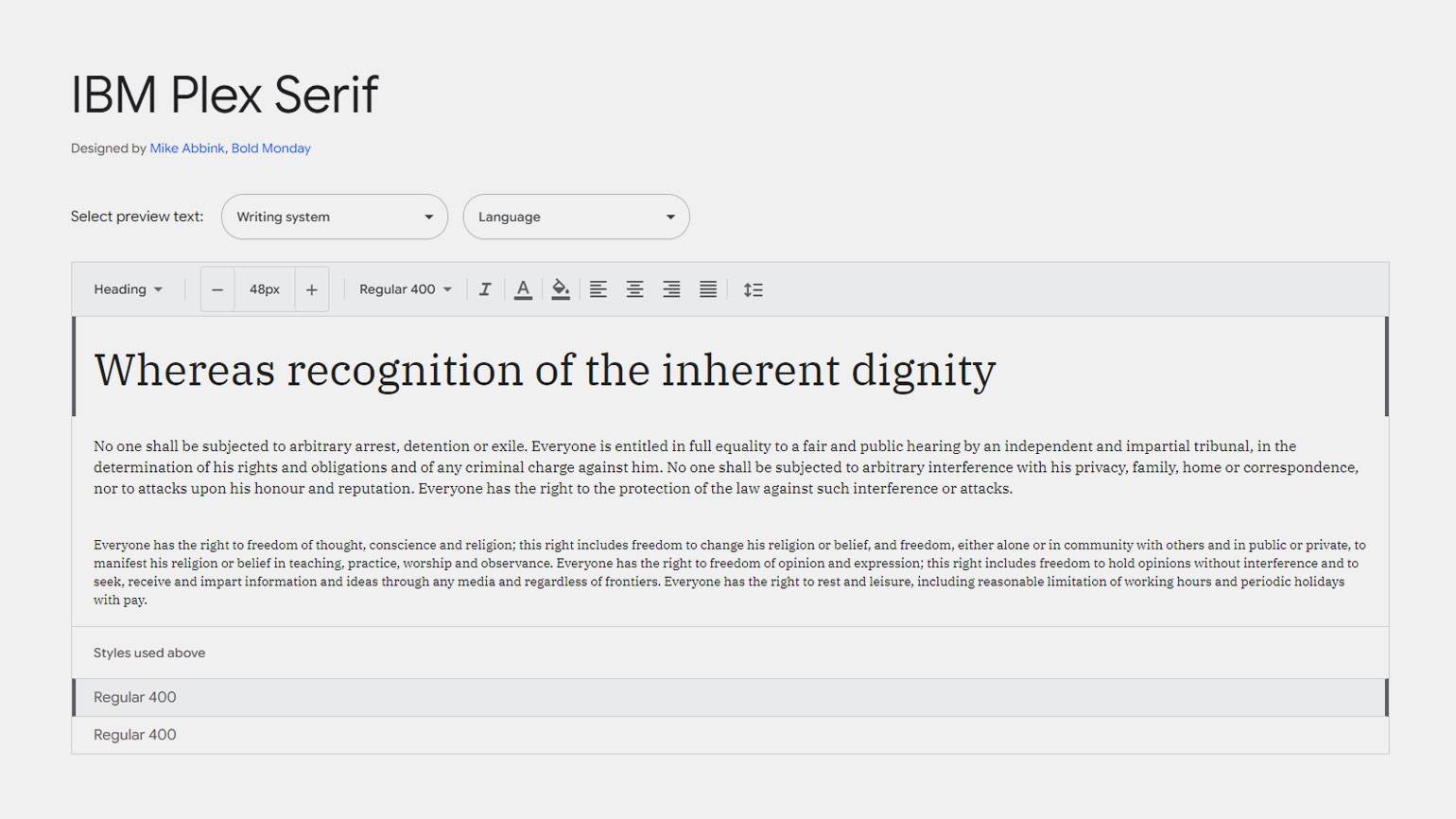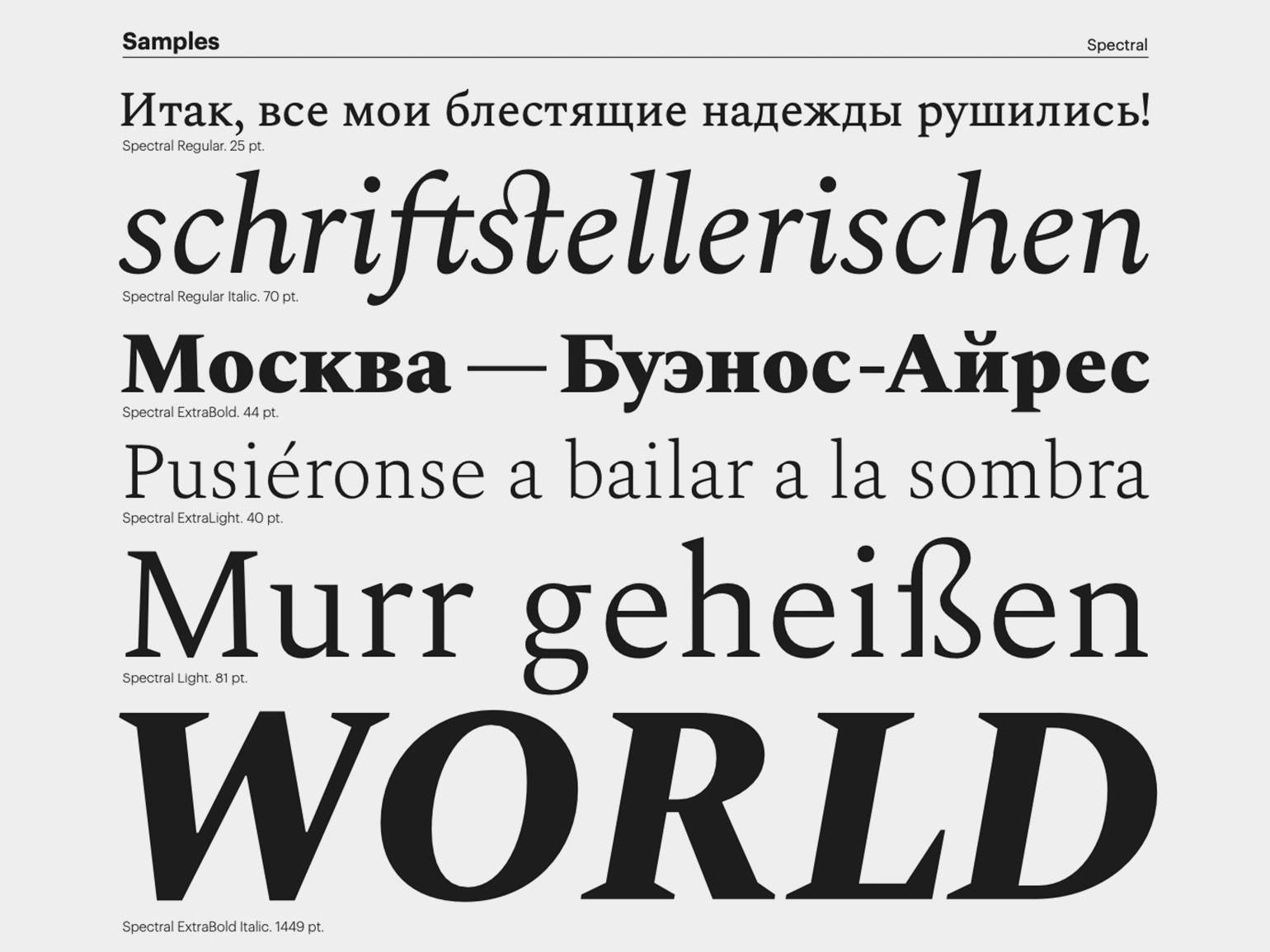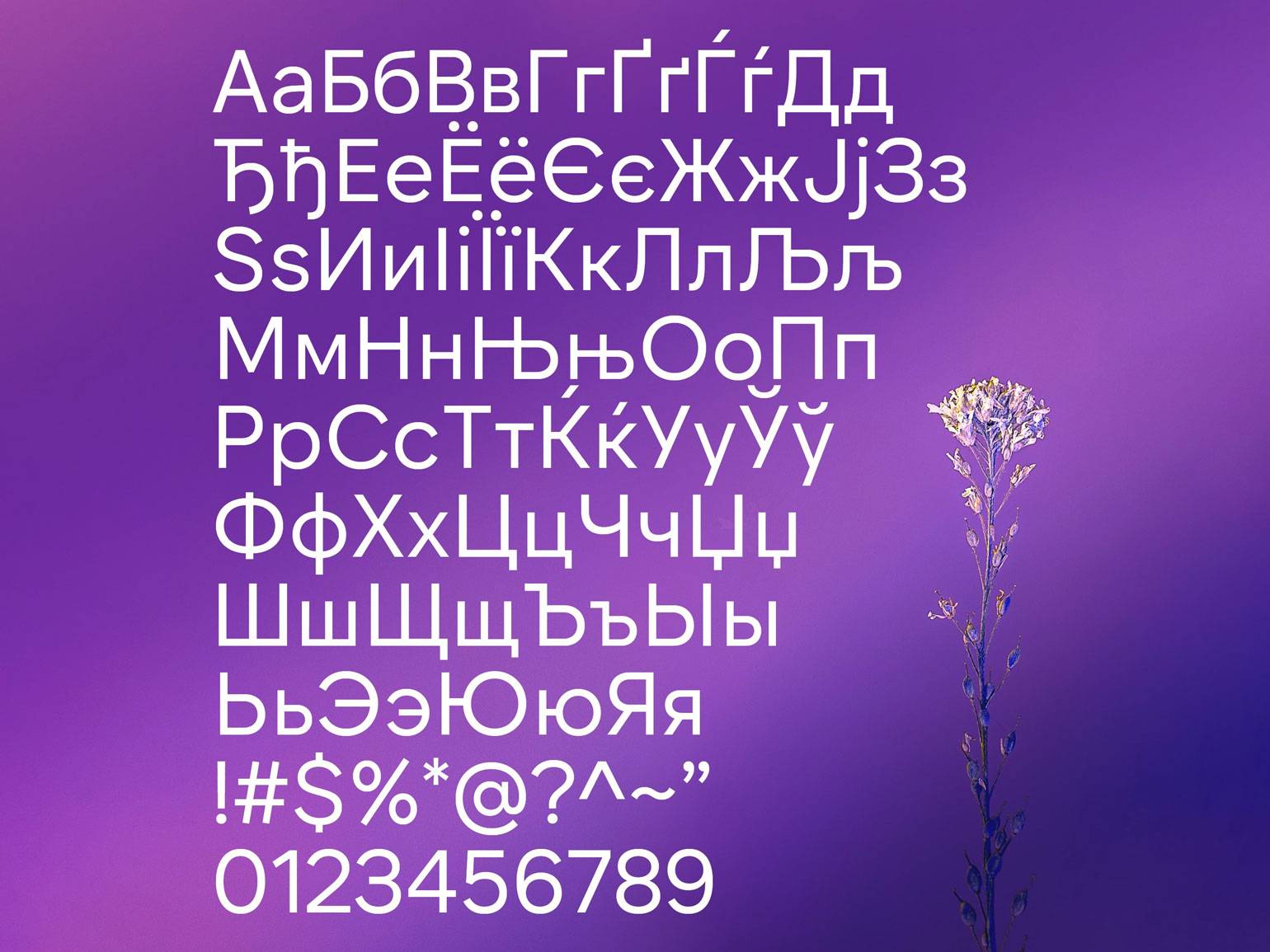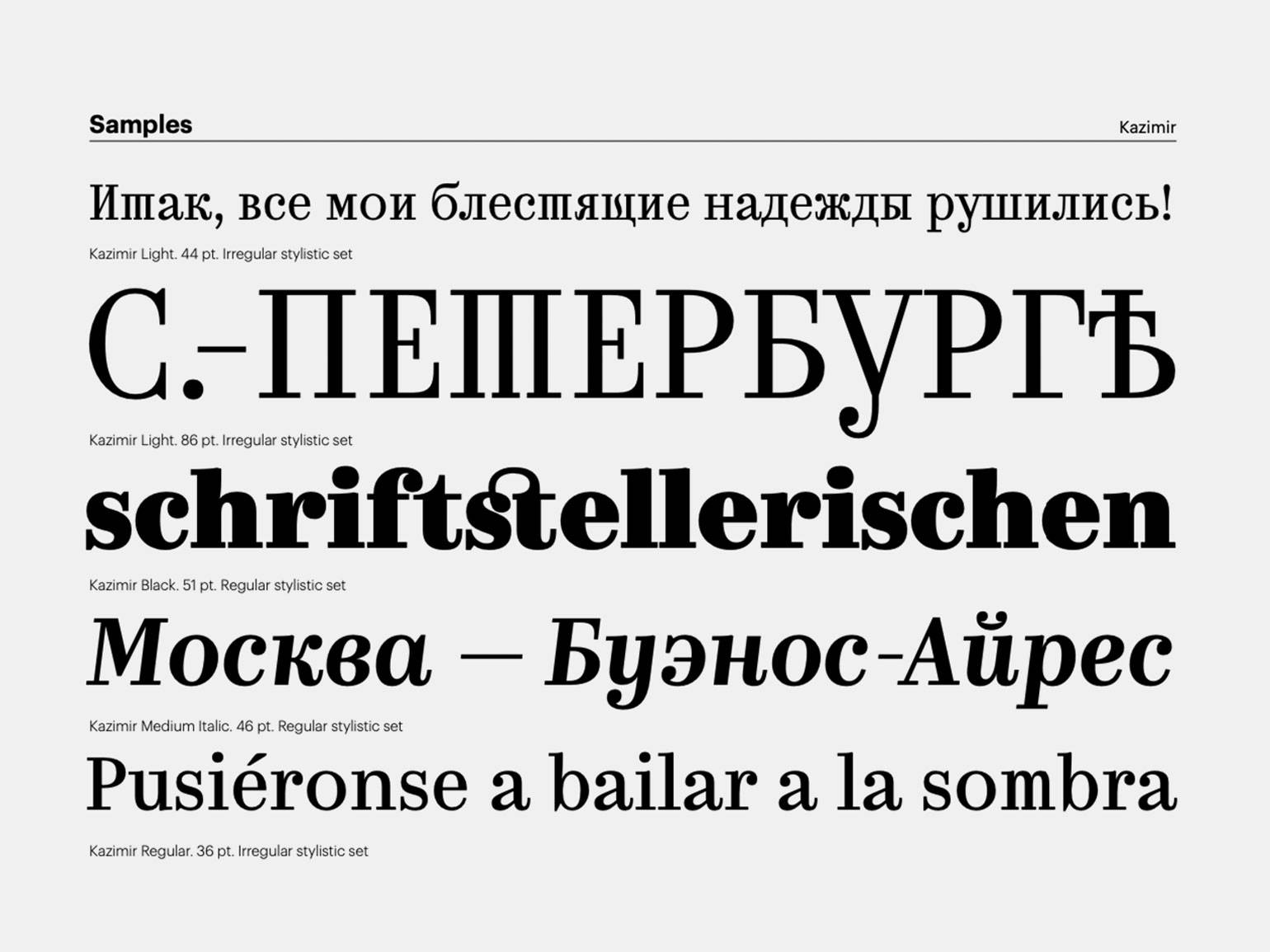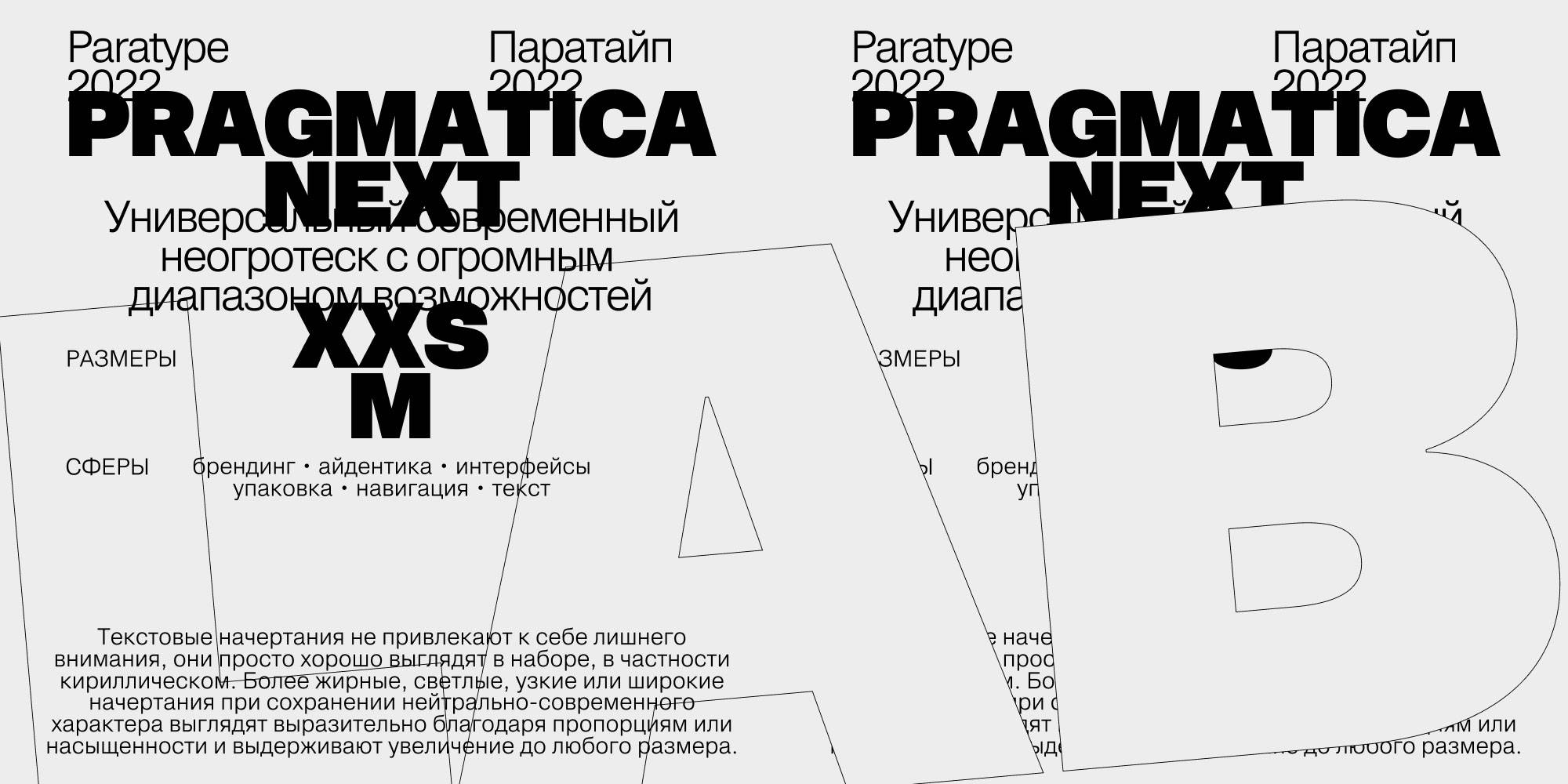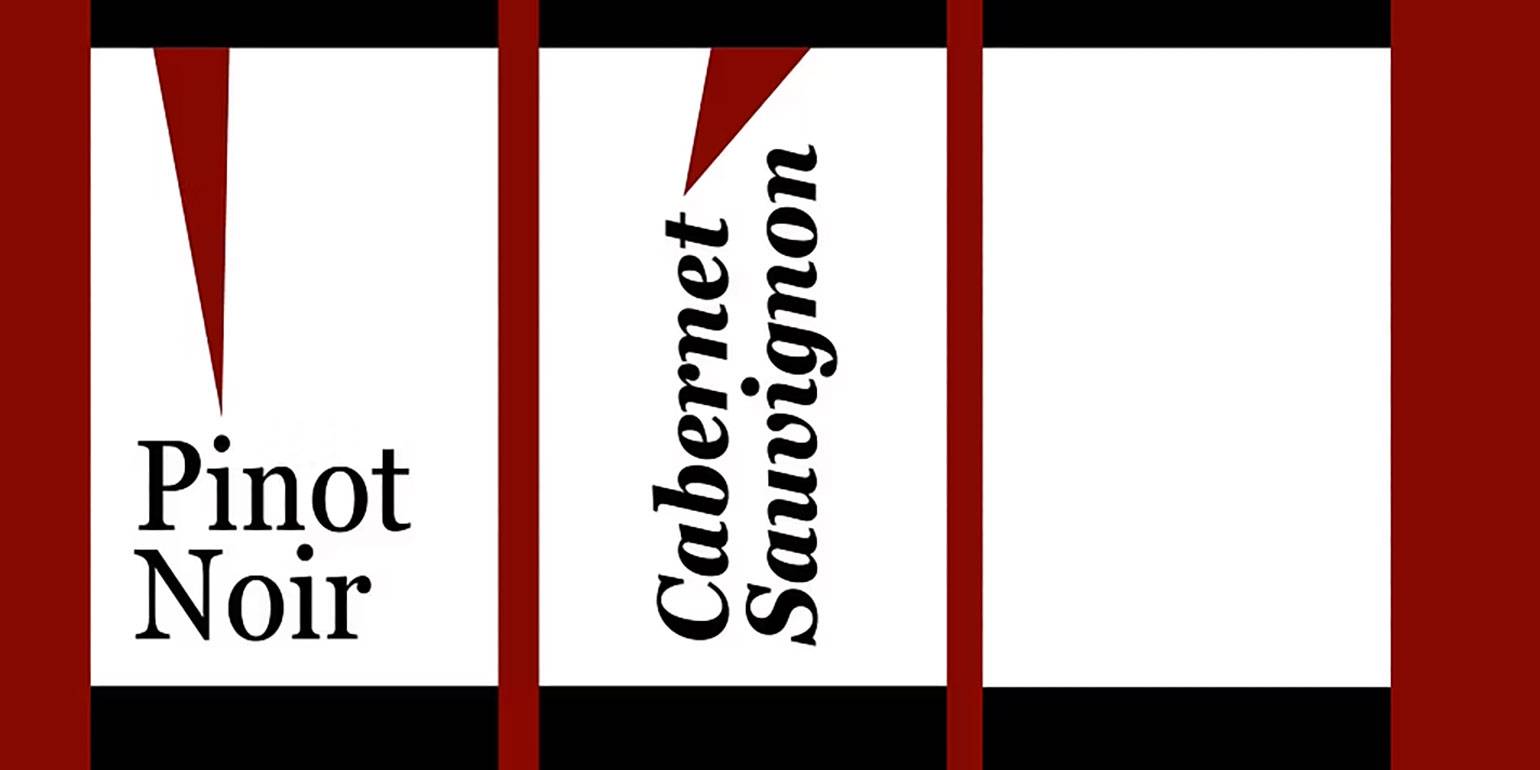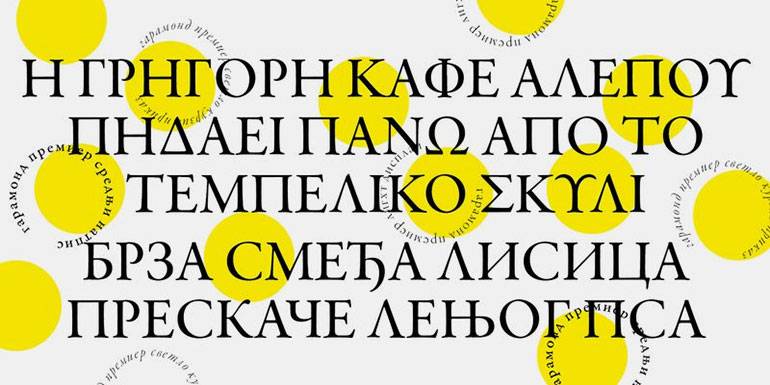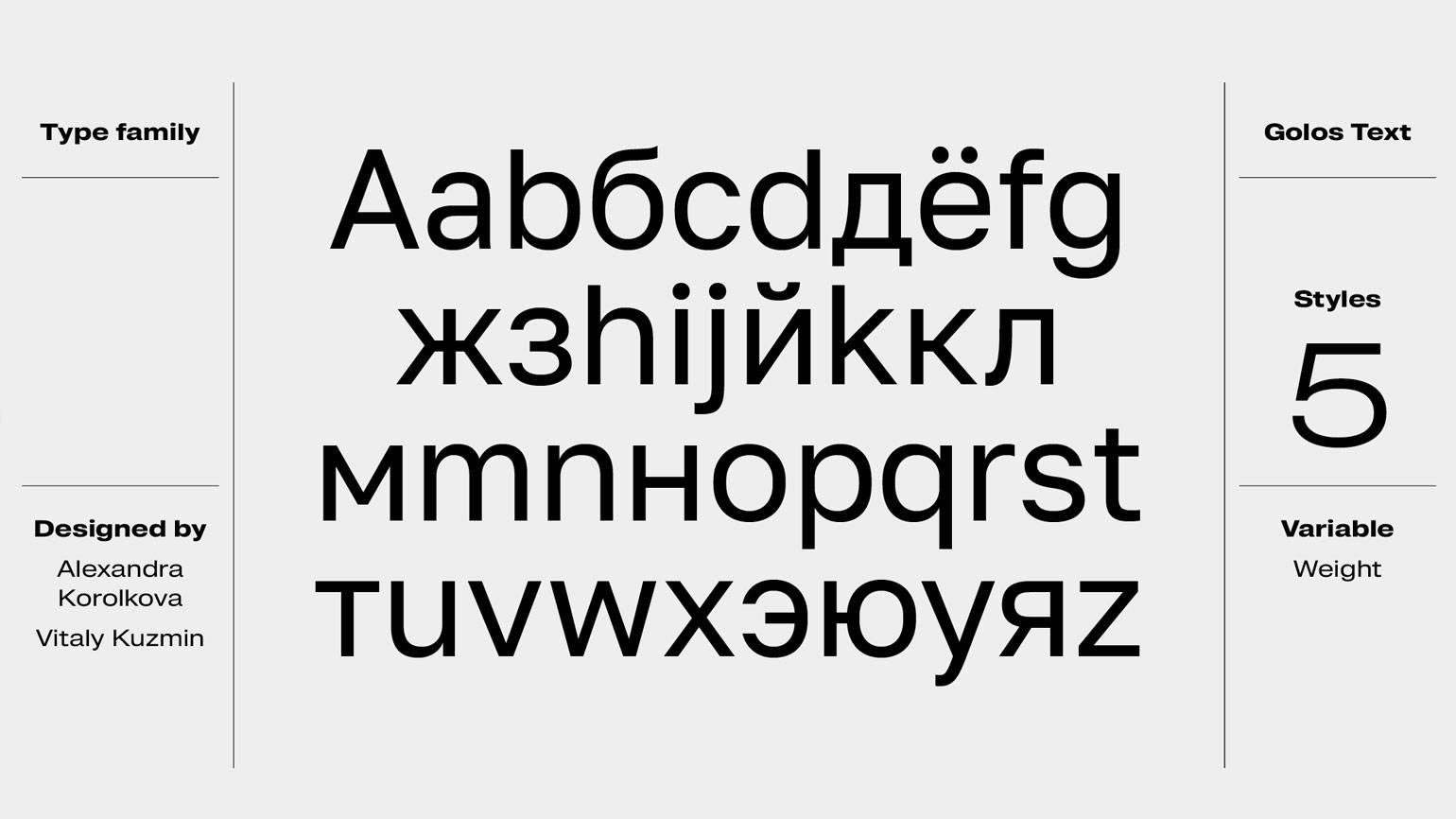
Базовый шрифтовой гардероб: 5 платных и 5 бесплатных гарнитур
Все главные шрифты на любой случай.
В распоряжении современного дизайнера есть почти бесконечное количество шрифтов. Можно подумать, что это предоставляет творческую свободу, но чаще происходит обратное — паралич выбора.
Гораздо более эффективная практика — владеть малым, но выверенным списком шрифтов, которые способны качественно решить любую задачу. Так, к примеру, делал Массимо Виньелли — он использовал только шесть.
Собрали список главных базовых шрифтов, которые закроют практически все ваши потребности и сместят фокус внимания с селектора шрифтов на дизайн.
Универсальный неогротеск
Неогротески — жанр шрифтов, который не уходит из трендов последнее столетие. Мы видим их везде: в логотипах корпораций, интерфейсах наших смартфонов, паспортах многих стран. Если и есть по-настоящему универсальная категория шрифтов, то это неогротески.
Зачем нужен
Неогротески несут в себе неуловимое ощущение завершённости и нужны там, где требуется строгость, совмещённая с уверенностью. При этом нейтральность их форм позволяет им быть уместными в абсолютно любых ситуациях.
Какой шрифт купить
Pragmatica Next от Paratype.
Pragmatica Next — переосмысление «Прагматики», знакового кириллического неогротеска по мотивам Helvetica. Обновлённая версия обладает огромным спектром вариативности: от ширины Compressed (XXS) до Extra Expanded (XXL) и от насыщенности Thin (100) до Black (900), благодаря чему она впишется в абсолютно любые сценарии использования.
Бесплатный шрифт в этом жанре
Golos Text от Paratype.
Golos Text — многофункциональный закрытый гротеск, подходящий и для длинных текстов, которые надо долго читать, и для айдентик. Доступна ось вариативности по насыщенности.
Его возможности не так безграничны, как у Pragmatica Next, но главного достоинства у него не отнять — он полностью бесплатен.
Старостильная антиква
Старостильные антиквы — подгруппа шрифтов с засечками XV — начала XVIII в. Их определяет малый контраст штриха, открытость апертур, наклонные оси овалов, асимметричные засечки и общая дуктальная природа форм.
Зачем нужна
Шрифты этого жанра чувствуют себя особенно уверенно в длинных текстах с историческим привкусом и в художественной литературе.
Какой шрифт купить
Garamond Premier Pro. Автор — Роберт Слимбах.
«Гарамон» — название семейства гарнитур, основанных на рисунках французских типографов шестнадцатого столетия Клода Гарамона. Garamond Premier Pro — цифровая версия Роберта Слимбаха с широчайшим спектром начертаний, включающих как насыщенность, так и оптические размеры. Они особенно полезны при работе со сложноструктурными изданиями.
Бесплатный шрифт в этом жанре
Spectral от Production Type.
Spectral разрабатывался по заказу Google для их офисного ПО — Google Docs и Google Sheets. Такое ТЗ сделало шрифт исключительно удобным для чтения в любых условиях, но такое утилитарное назначение не помешало Spectral быть красивой и элегантной гарнитурой.
Идеальный (!) геометрический гротеск
Человеческий мозг невольно стремится к гармонии и простым формам. С этой точки зрения геометрические гротески — самые «идеальные» и «правильные» шрифты. В основе большинства гарнитур этого жанра примитивные фигуры: круг, квадрат и треугольник.
Зачем нужен
Как и другие гротески, шрифты этого жанра достаточно универсальны. Однако в отличие от неогротесков графика геометрических не вызывает «швейцарских» ассоциаций, которые уместны не в каждом дизайне.
Какой шрифт купить
Futura PT от Paratype.
«Футура» — самый знаменитый геометрический гротеск, разработанный Паулем Реннером в 1927 году. Futura PT — наиболее полная кириллическая версия легендарного шрифта, состоящая из 25 начертаний от Thin до Extrabold: 16 нормальных и девять узких.
Изображение: Paratype
Бесплатный шрифт в этом жанре
NT Somic от NT Type.
NT Somic — современный, простой геометрический гротеск. Подходит для айдентики, текстов, визуальных коммуникаций, титров и многих других сценариев, где от шрифта не требуется привлекать к себе слишком много внимания.
Он не такой геометрический и яркий, как Futura PT, однако его простота и нейтральность может стать преимуществом.
Переходная антиква на каждый день
Переходная — самая привычная, известная антиква из всех: например, Times New Roman относится именно к этому жанру. Она умеренно контрастная, с симметричными засечками и вертикальными осями овалов. Из-за широкой распространённости этот жанр воспринимают как достаточно нейтральный вид шрифтов с засечками.